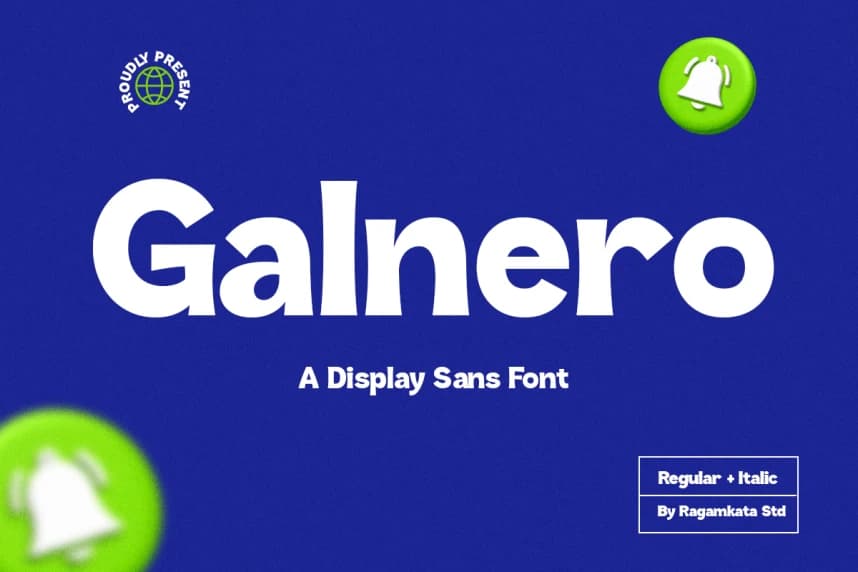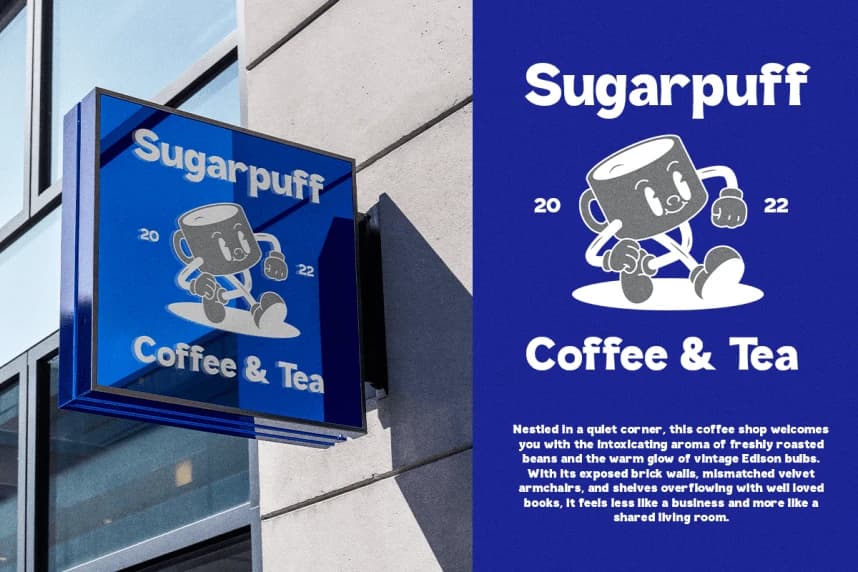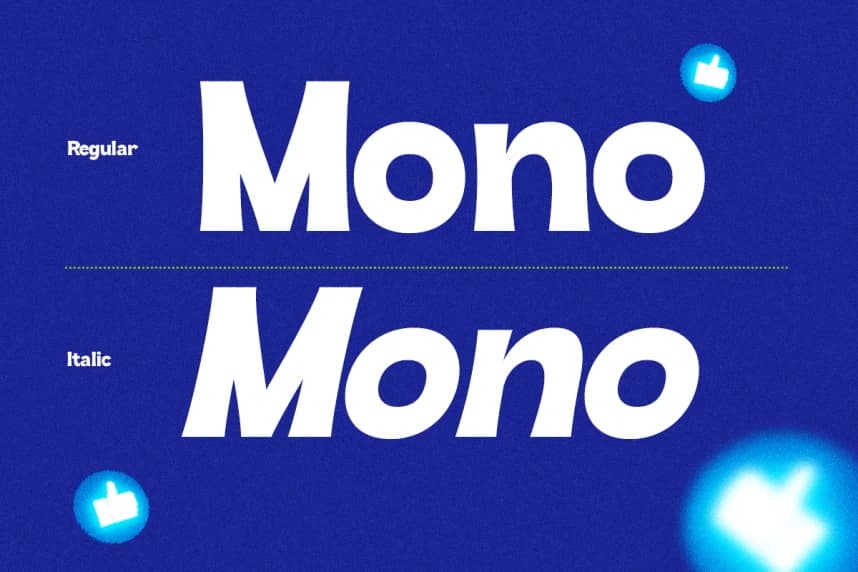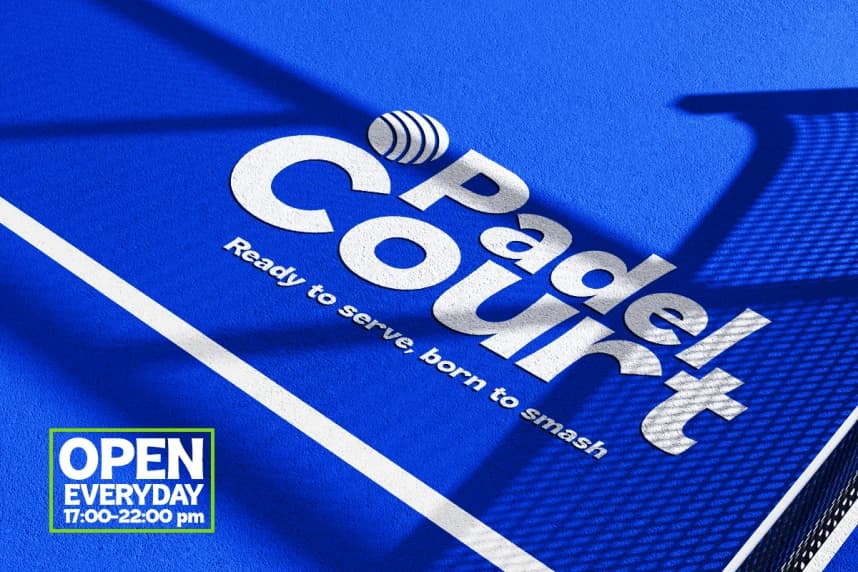
Galnero Font, temiz ve modern bir estetikle güçlü görsel etki yaratmak için tasarlanmış gösterişli bir sans fontudur. Sert harf biçimleri ve akıcı eğrilerle Galnero, hemen öne çıkan kendinden emin ve çağdaş bir stil sunar. Kalın yapısı mükemmel okunabilirlik sağlar, while mai
Galnero Font, temiz ve modern bir estetikle güçlü görsel etki yaratmak için tasarlanmış kalın bir gösterişli sans fontudur. Sert harf formları ve pürüzsüz eğriler ile Galnero kendinden emin ve çağdaş bir stil sunar ve anında fark edilir. Kalın yapısı, belirgin ve göze çarpan bir görünüm sürdürürken mükemmel okunabilirliği sağlar.